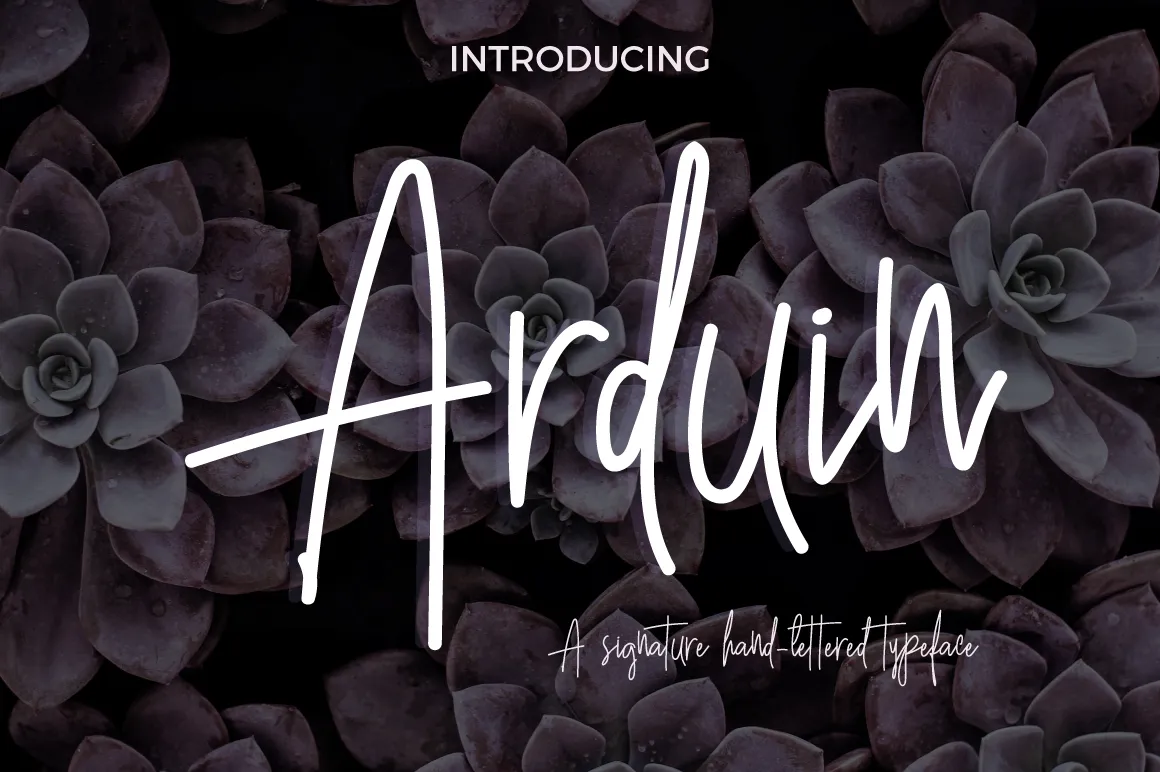
Arduin Script Font é uma elegante tipografia feita para dar ao design uma sensação amigável e moderna. Este tipo foi projetado pelo designer Paramajan com base na própria escrita do criador, que às vezes pode ser um pouco confusa, mas sempre é leitura fácil. A Arduin se refere a um amigo valente. Esta fonte perfeita para criação de logotipos modernos, identidades corporativas, etiquetas, adesivos e design de embalagens, além de ser uma ótima escolha para desing de roupas. Ela é ideal para designers que buscam um estilo único em seus projetos visuais.